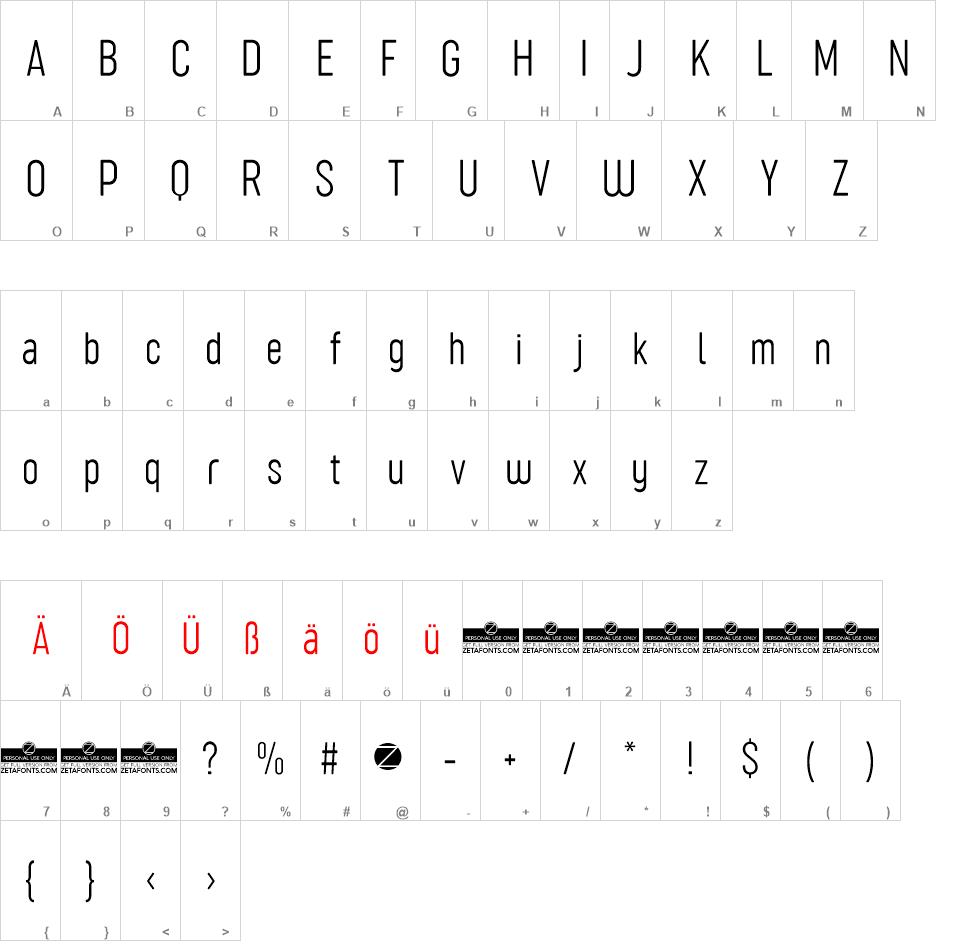
Sugo Pro Display
Sugo Pro ist eine komprimierte geometrische Grotesk mit einem robusten Körper, leicht abgerundeten Ecken und geradliniger Streetstyle-Haltung. Das robuste und robuste Design von Sugo macht es zur idealen Wahl für Sport-Branding und Street-Style Editorial. Leichtere Gewichte bieten eine gute Lesbarkeit bei kleinen Größen, während die regulären und kühnen Gewichte eher für Titel, Logo und Schlagzeilen geeignet sind.
Es wurde 2006 von Francesco Canovaro in zwei Gewichten (Normal und Extralight) entworfen und später von Cosimo Lorenzo Pancini als Vorlage für das Design der erfolgreichen Coco-Goose-Schrift von Zetafonts verwendet. Im Jahr 2018 wurde die Familie von Andrea Tartarelli komplett umgestaltet, wobei das ursprüngliche Glyphen-Set auf kyrillisch und griechisch erweitert wurde und drei zusätzliche Gewichte und Kursivmarken hinzugefügt wurden. Die restaurierte und überarbeitete Version, Sugo Pro Classic genannt, enthält auch vollständige Open Type-Funktionen für Positionsfiguren, Alternates und Small Caps und stellt alternative Glyphenformen wieder her, die von Canovaro für den ursprünglichen Sugo erstellt wurden und als Stylistic Alternates zugänglich sind.
Eine begleitende Schrift, Sugo Pro Display, verwendet diese Alternativen als Basis-Glyphen und bietet ein engeres Kerning, ideal für die Display-Verwendung und das Logodesign.